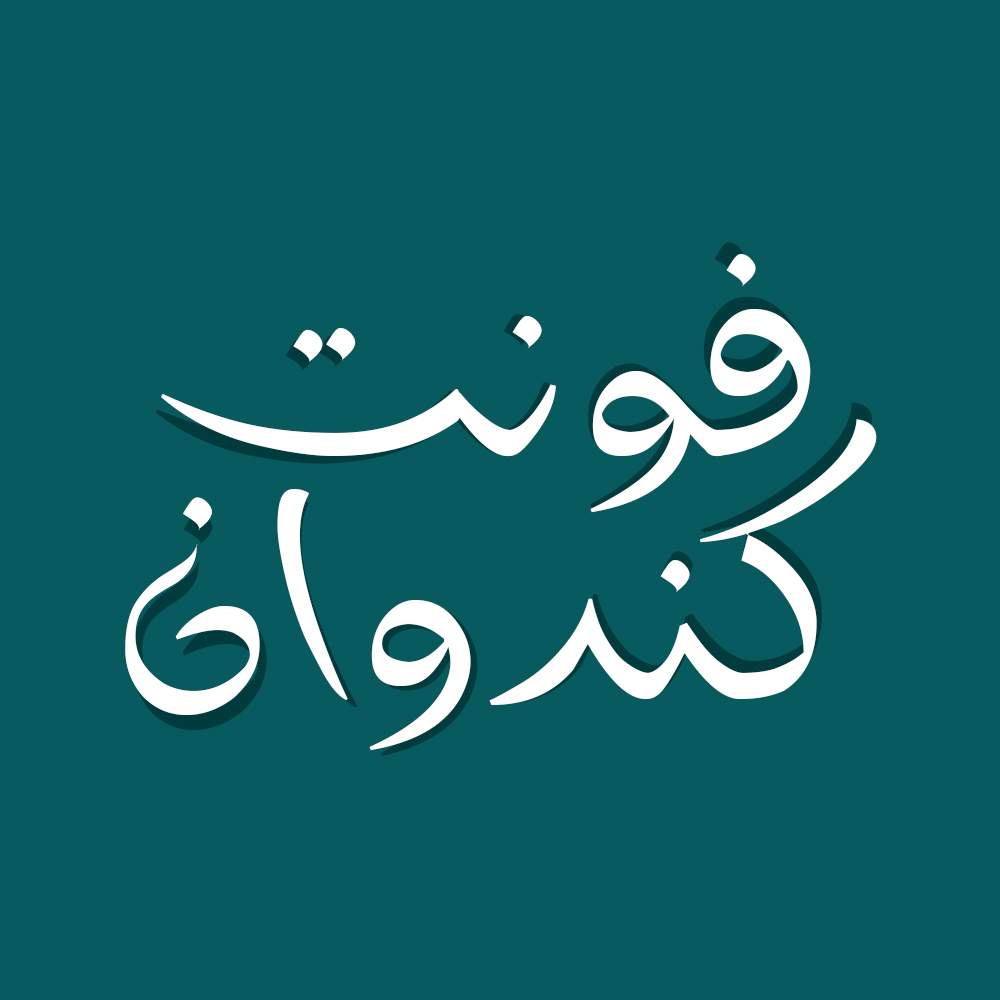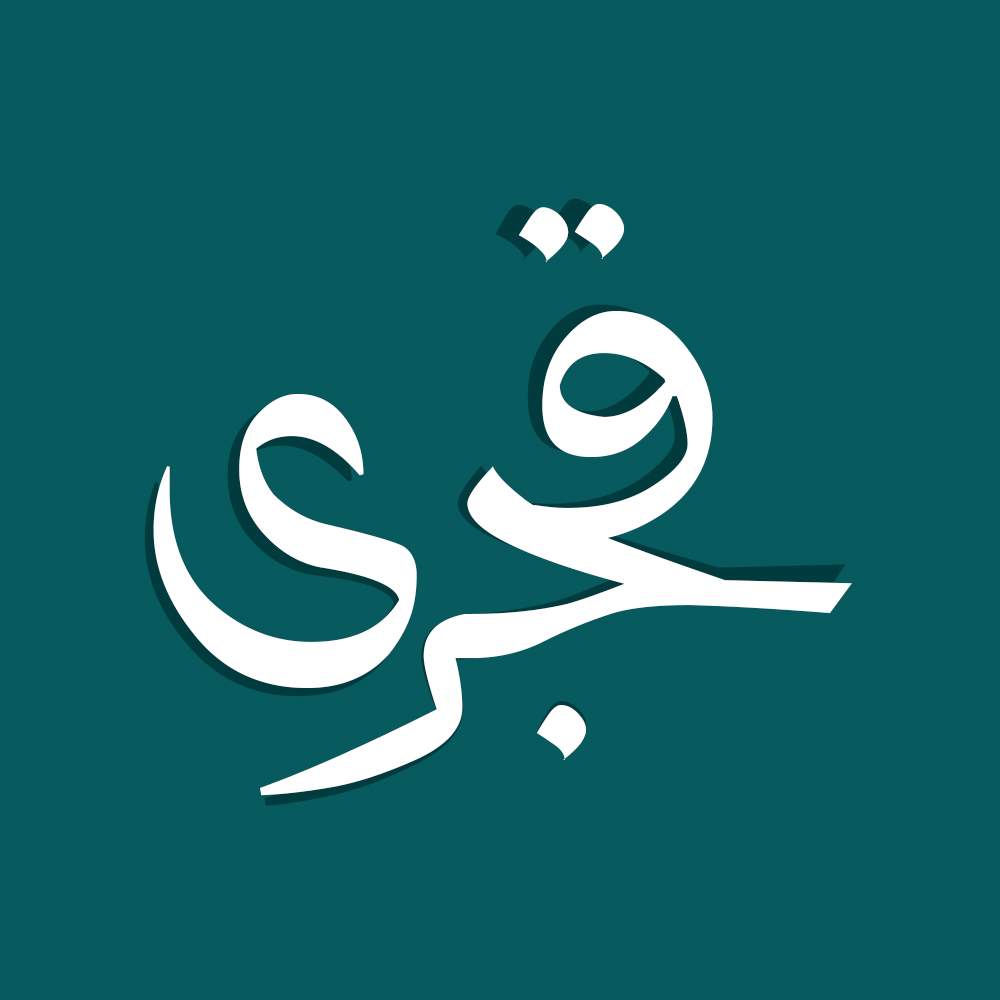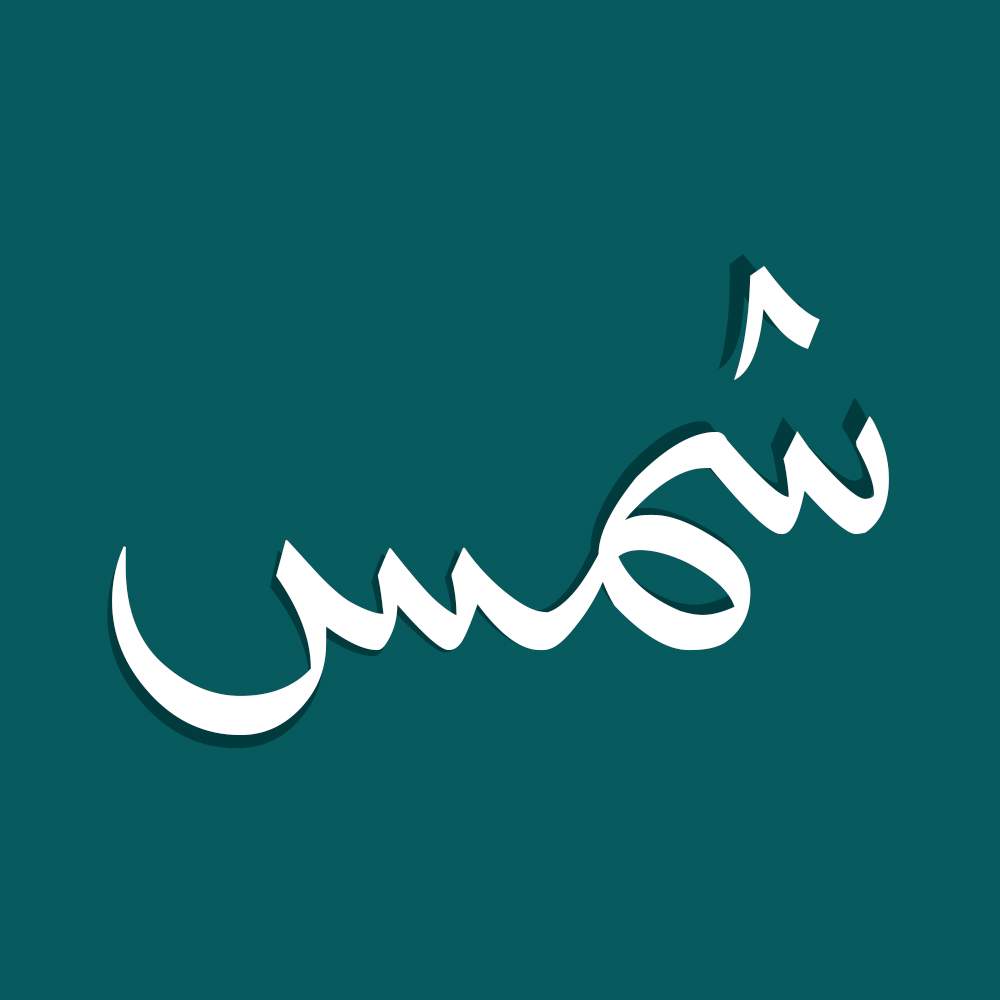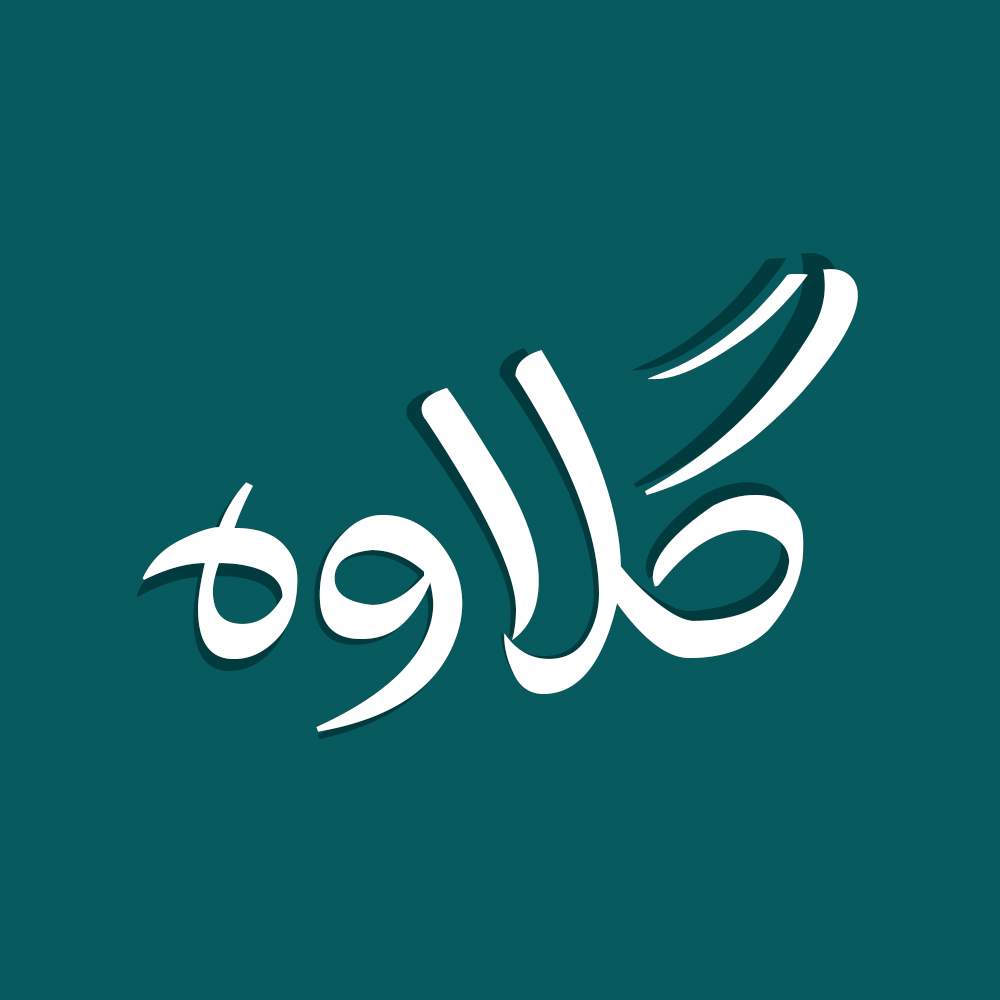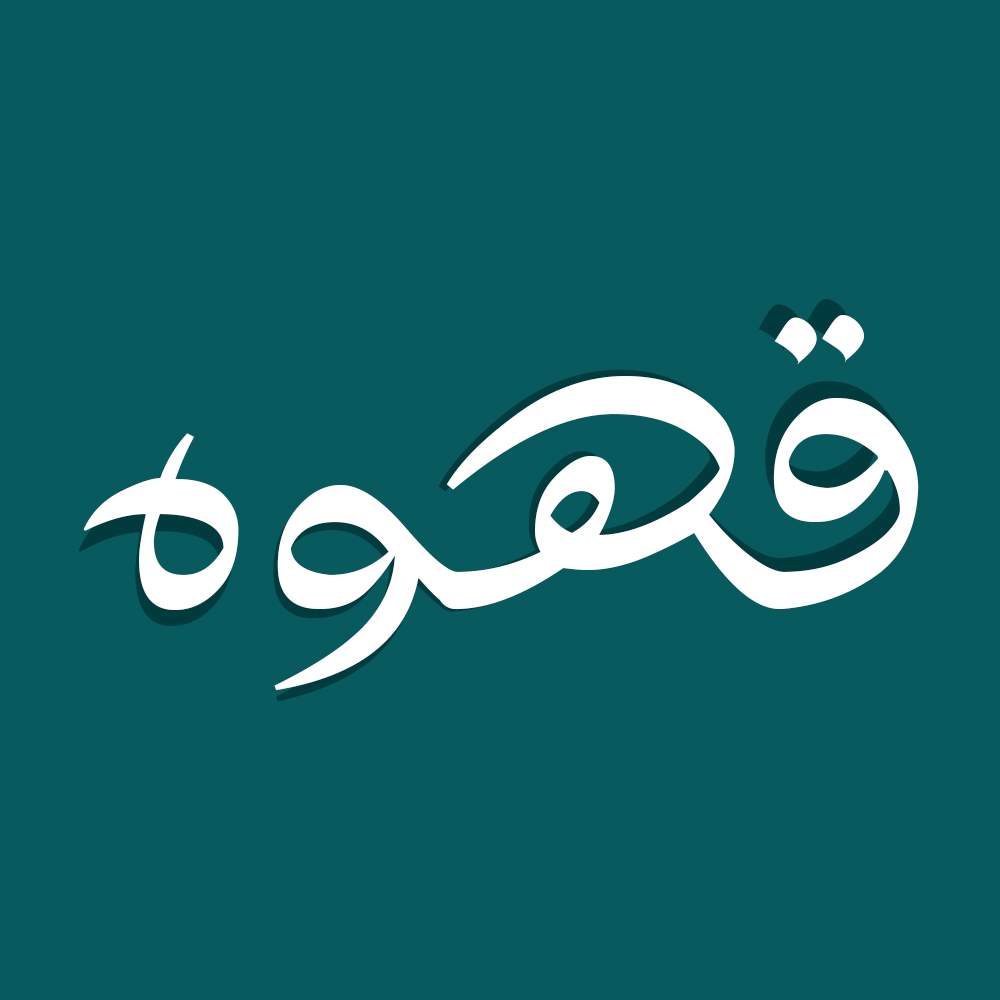
فونت فارسی کندوان Kandovan Font
فونت فارسی کندوان یک فونت نمایشی با شخصیتی جسور، خلاق و مستحکم است که با الهام از سبک‌های سنتی ایرانی و ترکیب آن با مدرن‌ترین المان‌های…
فونت فارسی کندوان یک فونت نمایشی با شخصیتی جسور، خلاق و مستحکم است که با الهام از سبک‌های سنتی ایرانی و ترکیب آن با مدرن‌ترین المان‌های طراحی گرافیکی ساخته شده است و برای طراحان گرافیک، تولیدکنندگان محتوا، تایپوگرافی و طراحی لوگو انتخابی بی‌نظیر می‌باشد. فونت داروغه با حال‌وهوای قدیمی خود، حس خاطره و نوستالژی را تداعی می‌کند. وقتی کاربر متنی را با این فونت می‌خواند، به یاد تابلوهای قدیمی شهر، پوسترهای فرهنگی گذشته می‌افتد. همین ویژگی باعث می‌شود طراحی شما متفاوت، احساسی و ماندگار شود. در ادامه برای شما نمونه تایپ های این محصول حرفه ای رو آماده کردیم که می‌توانید مشاهده کنید.
• طراحی لوگوهای خاص با هویت ایرانی
• تایپوگرافی و پوسترهای فرهنگی و هنری
• جلد کتاب و مجله با حس نوستالژی
• طراحی بنر تبلیغاتی و شبکه‌های اجتماعی
• استفاده در برندینگ برای نمایش اصالت و اعتماد
• مناسب استفاده در تابلو های چلنیوم و طراحی حروف
پیشنمایش و نمونه تایپ های فونت کندوان